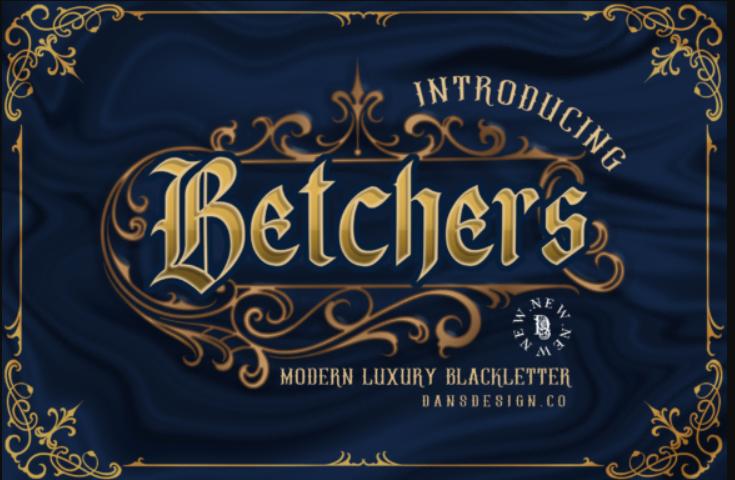
[Creativefabrica] Betchers Font (Dansdesign)
Betchers - это великолепный черный шрифт, который выглядит одновременно торжественно и изысканно. Это будет прекрасный выбор для татуировок, цитат, журналов, упаковки продуктов и многого другого!